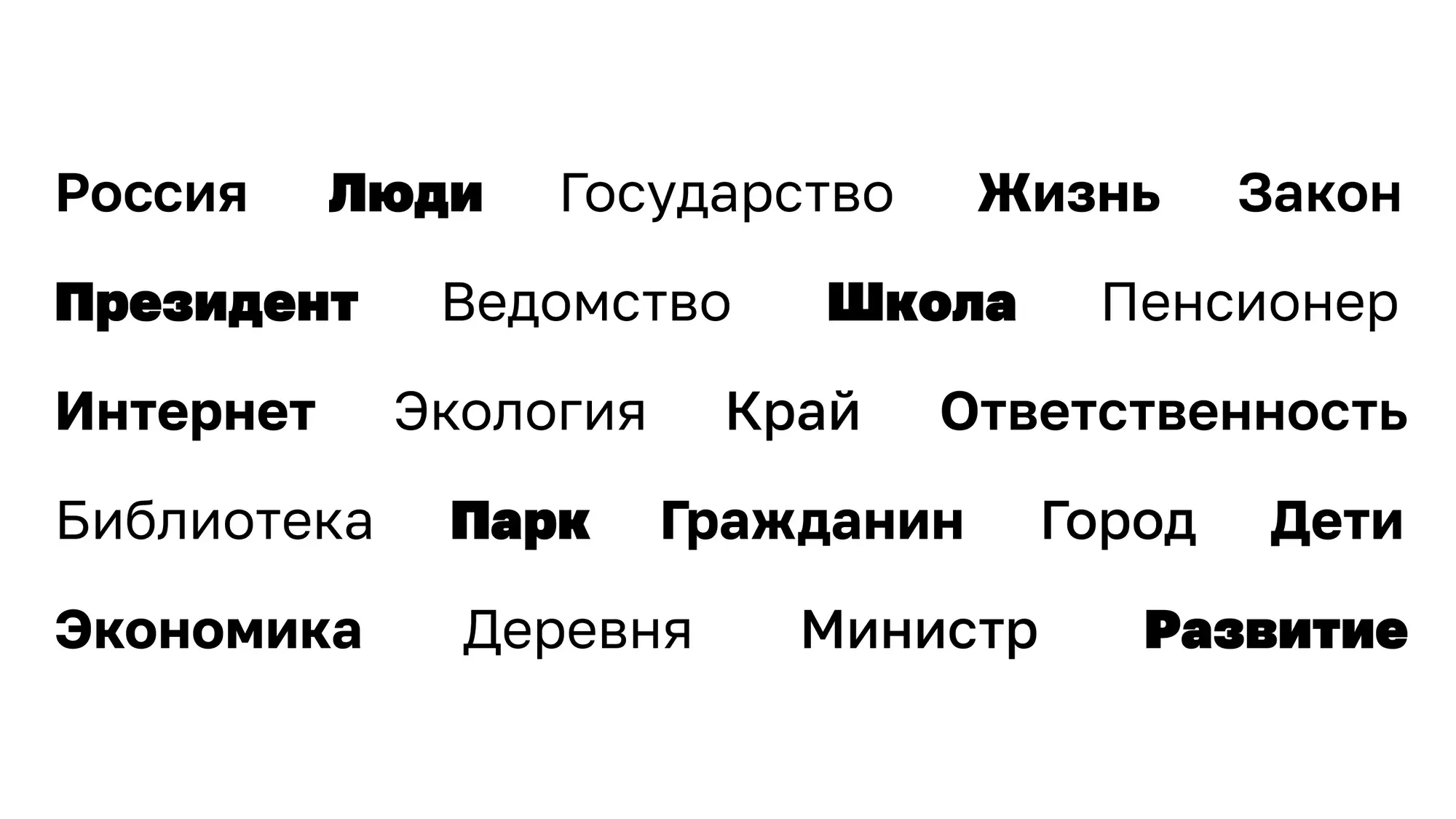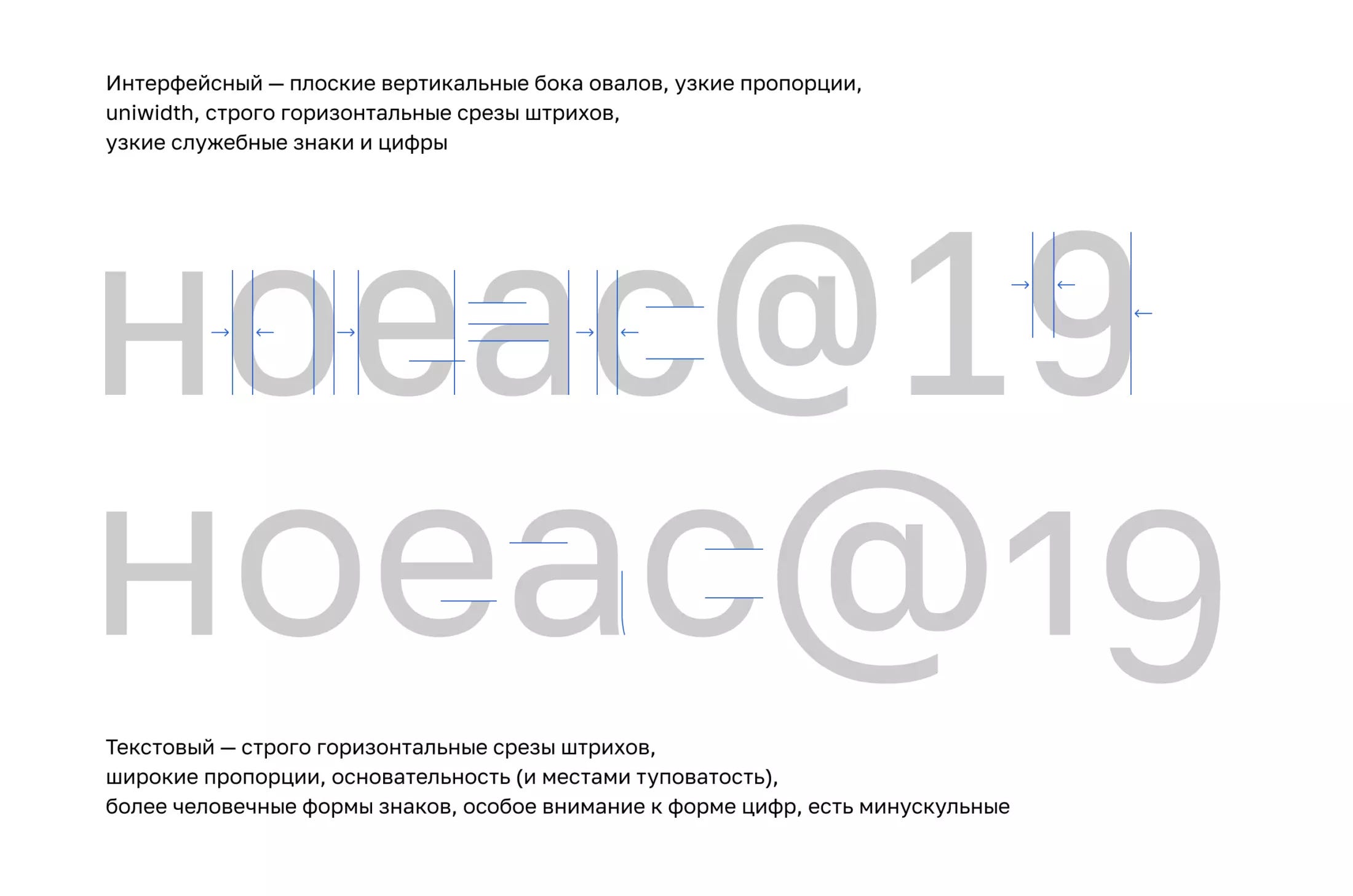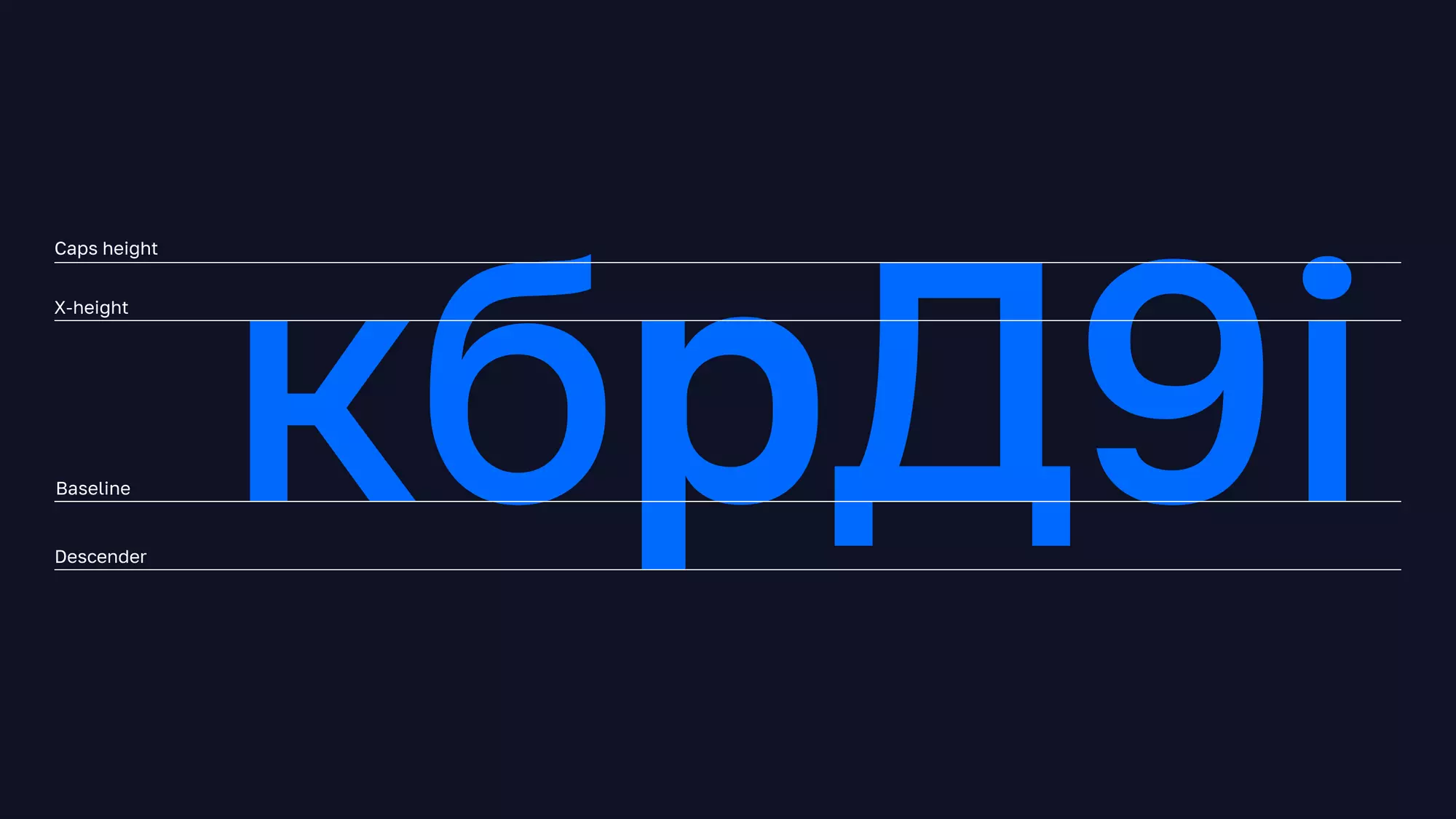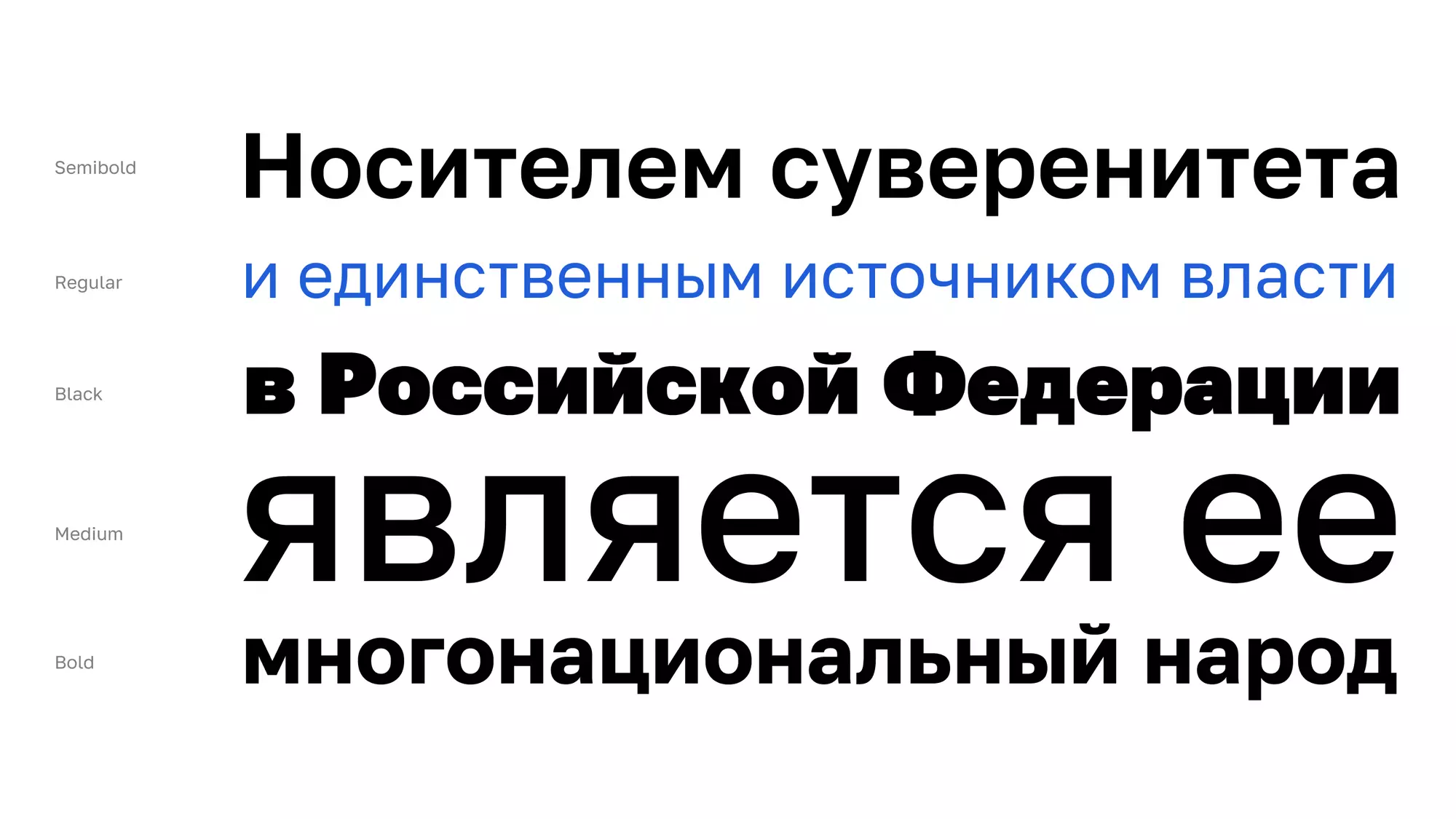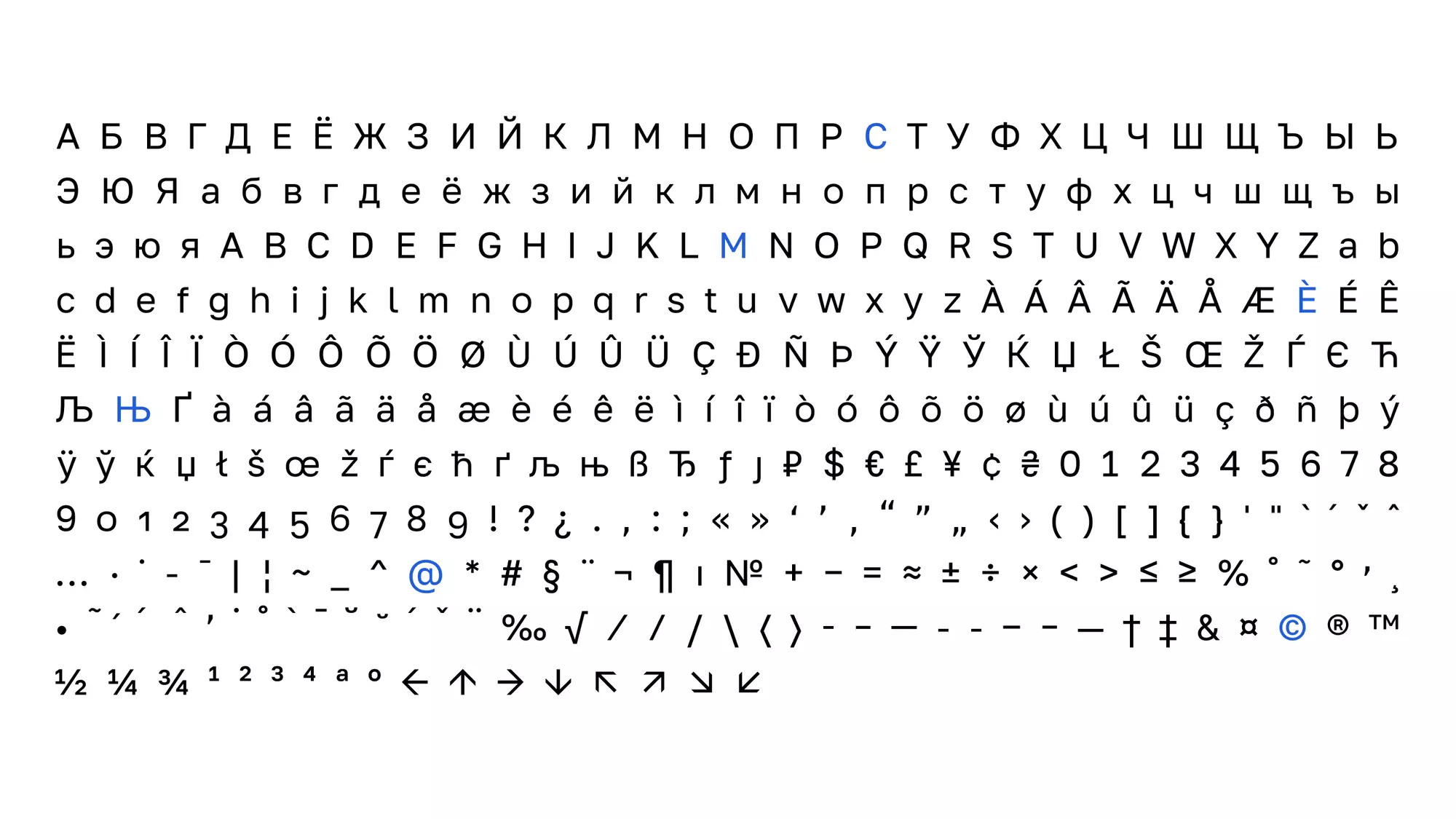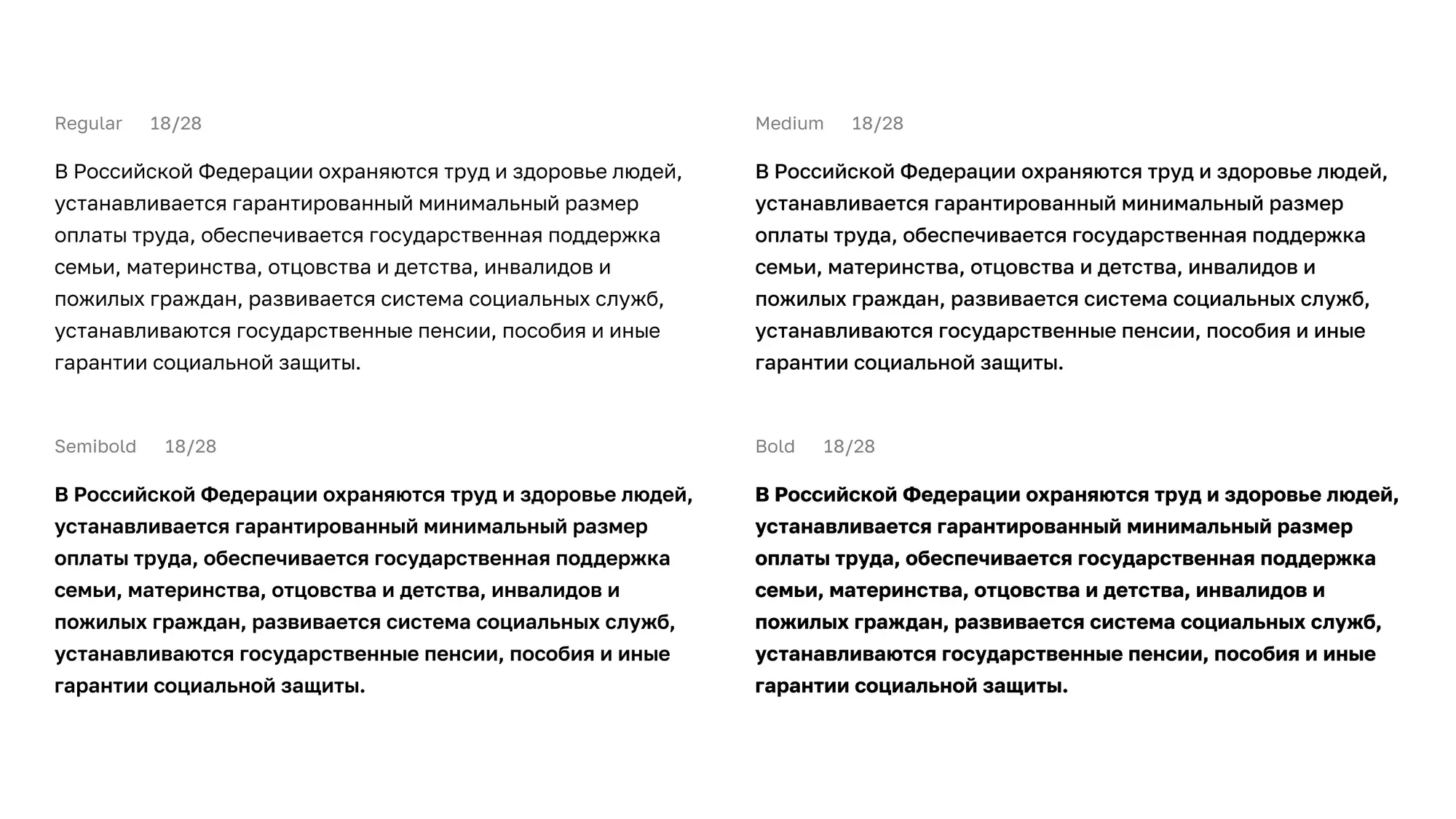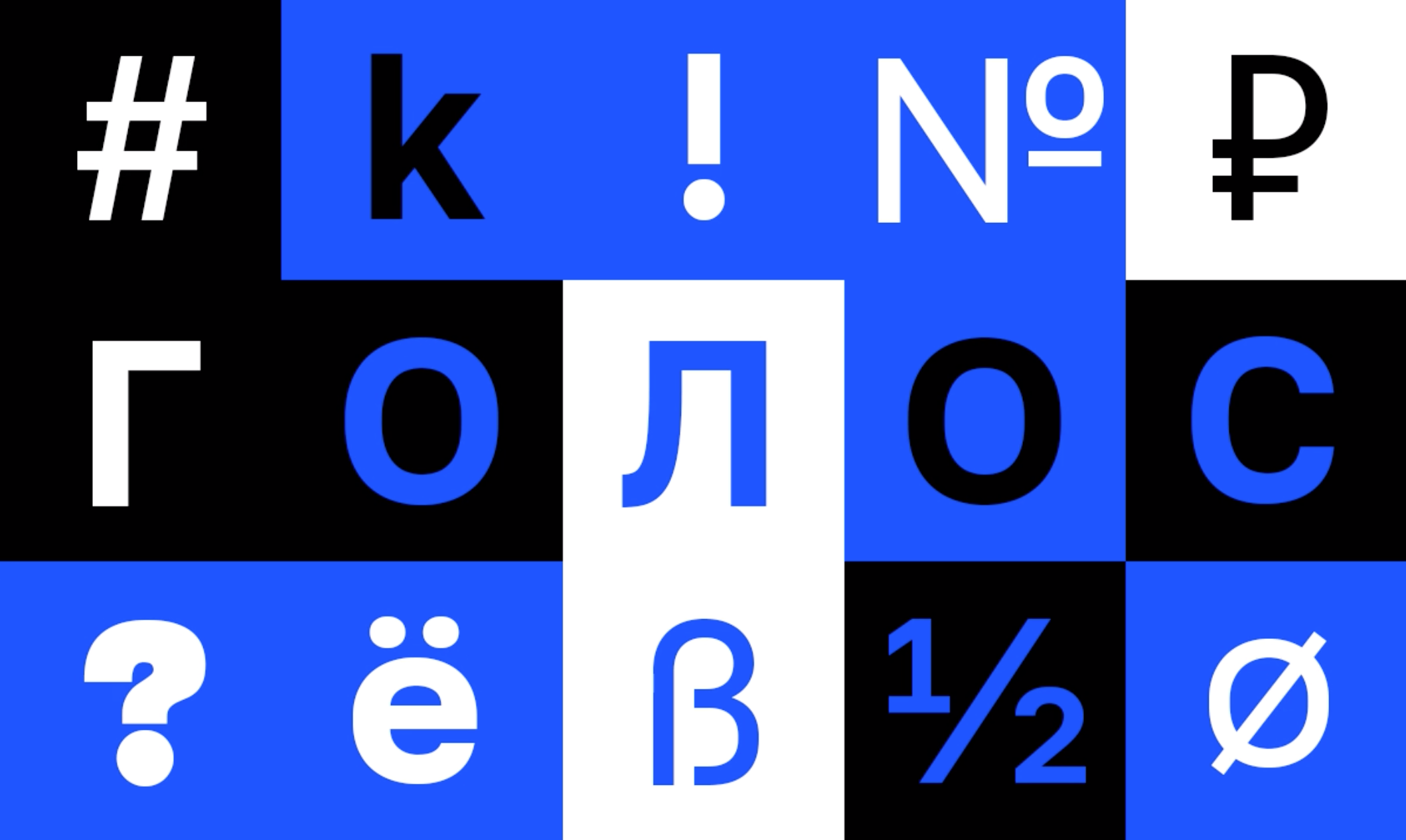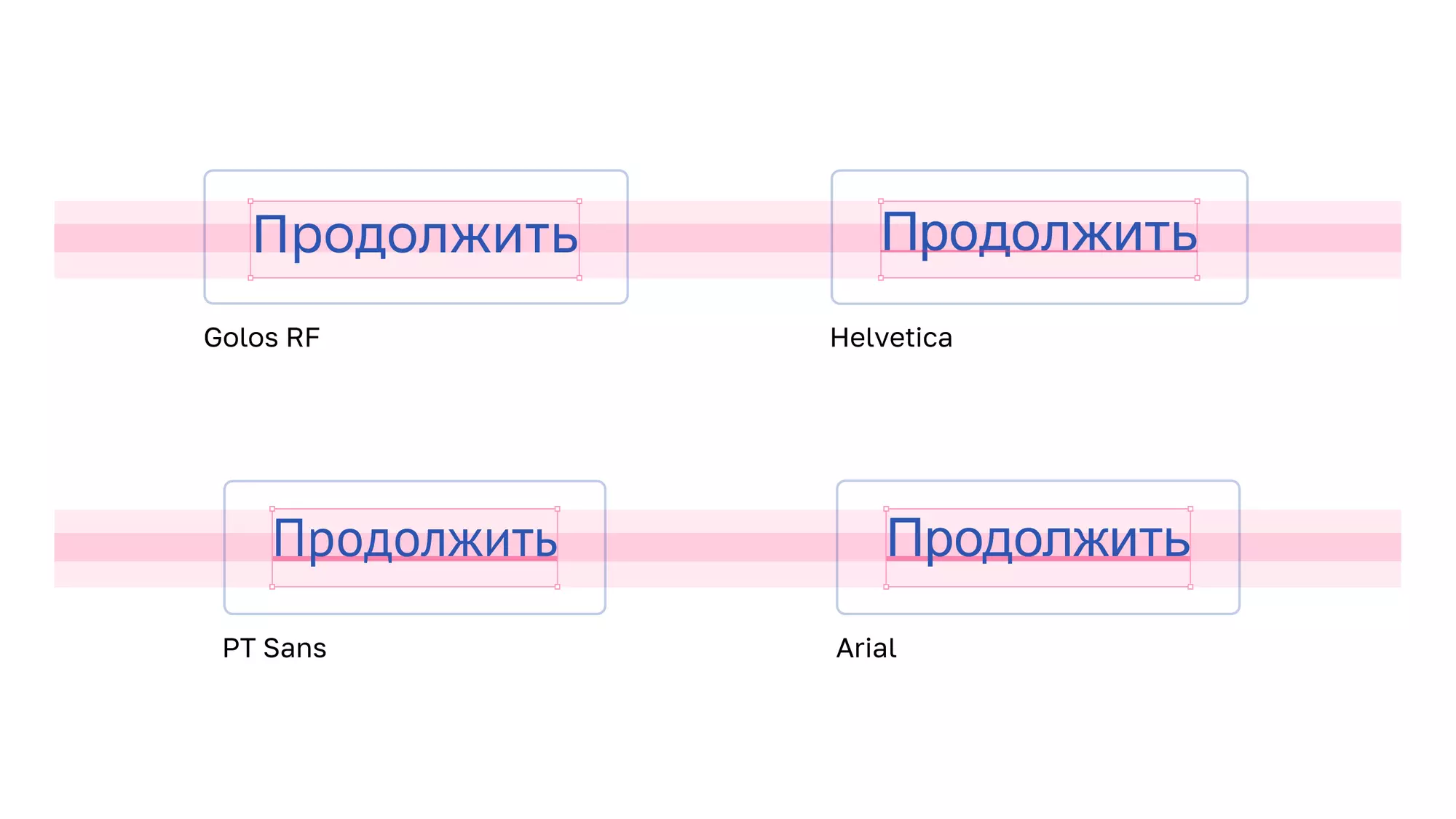
Как «Смена» создавала шрифт для государства в интернете
Стас Поляков, креативный директор дизайн-компании «Смена», которая с 2016 года занимается созданием дизайн-системы для всех государственных сайтов, рассказал, как родился шрифт Golos RF и зачем он понадобился.
Работу над шрифтом мы начинали вместе с коллегой Тимом Чёрным. В итоге получившимся шрифтом вскоре будут «говорить» все официальные сайты — от федеральных министерств и ведомств до интернет-площадок муниципальных властей.
Зачем дизайн-системе шрифт
В основе любой дизайн-системы лежит шрифт. Потом на него мало кто обращает внимание, особенно если он хорош и действительно лежит в основе той системы, в которой используется. Но начинается всё именно с него. Шрифт — это на­чаль­ная точ­ка, ДНК, мо­ле­ку­ла лю­бо­го ди­зайн-про­ек­та. И шрифт должен не втискиваться в систему, а быть её основой.
Кроме того, шрифт своим рисунком создаёт характер, который работает как на интонацию, так и на узнаваемость. Интонация и громкость шрифта должны быть умеренными — им мы говорим не только в приятные и восторженные моменты, но и в серьёзные и ответственные, когда человеку срочно нужно получить информацию или мы читаем серьёзную новость.
Зачем нужна узнаваемость для государства? Она помогает создать «доверенную зону», чтобы со временем каждый понимал, что он находится именно на государственном сайте и написанному можно верить. Такая узнаваемая доверенная зона важна как для сайтов с госуслугами, где пользователи оставляют свои личные данные, так и для справочных или новостных сайтов, где новости могут подделывать.
Также у шрифта в цифровой среде есть ряд критериев для корректной работы в интерфейсах: сглаживание (для экранов с небольшим разрешением), плотность и рисунок (которые влияют на читаемость), ширина набора (особенно важна для русского языка с длинными словами) и другие. Всё это мы старались учесть в работе над шрифтом и будем улучшать в будущем.
С чего мы начали
Какой шрифт должен быть в основе дизайн-системы Российской Федерации? На этот вопрос мы отвечали вместе со шрифтовым дизайнером Александрой Корольковой и компанией «Паратайп». Александра не только практик и теоретик кириллического шрифтового дизайна, но и лауреат премии имени Шарля Пеньо (2013), вручаемой ATypI (Международной типографической ассоциацией) раз в несколько лет дизайнеру до 35 лет «за выдающийся вклад в шрифтовой дизайн».
Обсуждение задачи начали «издалека», потому что говорить о шрифте отдельно от системы, в которой он будет применяться, невозможно.
Во-первых, создание дизайн-системы — это построение структуры и логики, по которой будет работать государство в цифровом, межплатформенном пространстве, взаимодействуя с очень широким кругом людей.
Во-вторых, создание цифрового образа государства, который можно узнаваемо передать в каждом новом элементе структуры. Это как придумать «Лего», состоящее из кусков реальной жизни.
С самого начала мы определили несколько принципов. Без принципов в целом тяжело, а в создании дизайн-системы — вообще невозможно. Остановиться стоит на одном: всё, что хорошо для людей, хорошо для государства. Остальные принципы и ориентиры естественным образом вытекают из ориентации на людей.
Например, «очевидность и понятность». Принцип сам по себе кажется простым: классно быть понятным. В нашем случае, применяя этот принцип на деле, нужно держать в голове широту и разнообразность аудитории, которая не оставляет никакой возможности её описать.
Выбирать готовое или создавать
Когда встаёт вопрос о выборе шрифта, всегда есть вариант взять что-то готовое и проверенное временем. Так происходит чаще всего. Но мы пошли по другому пути. Мы решили нарисовать новый шрифт, придерживаясь принципа Cyrillic First. И на это у нас было несколько причин.
Ни один существующий шрифт невозможно сделать своим, а государственный шрифт должен быть целиком и полностью отдан только в официальное использование (помните скандал с использованием Times New Roman?). Во-вторых, люди создали много шрифтов, решая разные задачи. Но нашу задачу, по крайней мере в кириллице и для русскоязычного мира, не решал ещё никто. Именно поэтому мы обратились в «Паратайп» к Саше Корольковой.
Обычно шрифты рисуются сначала под латиницу, а потом адаптируются под кириллицу. Отсюда очень много странных, иногда кривых и «облатиненных» решений в кириллице одного и того же шрифта. Также часто характер, который заложили в латинице, вообще не проступает в кириллице.
Мы же претендуем на главный цифровой шрифт о государстве российском. Поэтому мы рисовали изначально кириллическую версию. Во-первых, иметь собственный нарисованный под кириллицу шрифт дешевле, чем платить за лицензию бесконечно. Во-вторых, с собственным шрифтом у нас появляются широкие возможности настраивать важные для кириллицы и прикладных задач моменты. В-третьих, мы смогли сделать вариативный шрифт, который позволяет тонко настраивать его жирность.
Как мы рисовали шрифт
Golos RF уже можно называть официальным шрифтом Российской Федерации. Теперь он — голос государства в интернете, а со временем, может быть, выйдет и в офлайн. Сейчас мы уже используем его на практике, одновременно проверяя на удобочитаемость и апгрейды.
В нашем распоряжении пока только текстовая версия шрифта. Вскоре появится ещё дисплейная (для крупных наборов, заголовков), сериф (для набора долгих текстов и документов), моно (для кода).